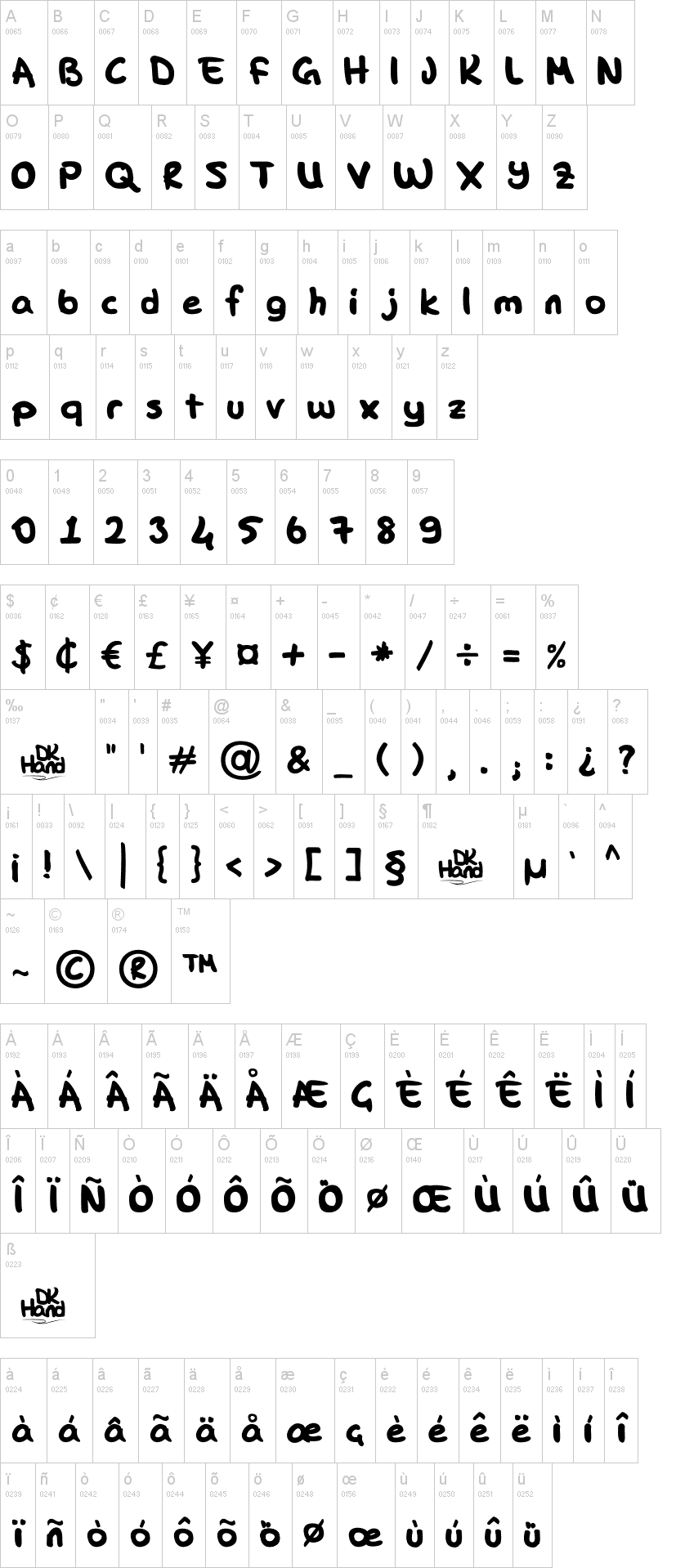
DK Hand
DK Hand 是一种手写风格的字体,具有自然、流畅、粗犷等特点。该字体由来自丹麦的设计师Donkey Kong设计,因此得名DK Hand。该字体包含大写字母、小写字母、数字和一些标点符号,适合用于海报、书籍封面、标志、广告等设计项目。该字体的使用可以增加设计作品的个性和独特性,让设计更生动有趣。
DK Hand是一款非常不错的手写艺术字体,具有很好的视觉感,适合于文化类的宣传设计、商业类品牌的广告和产品包装设计以及个性化文字排版等较多场景。
DK Hand字符映射图